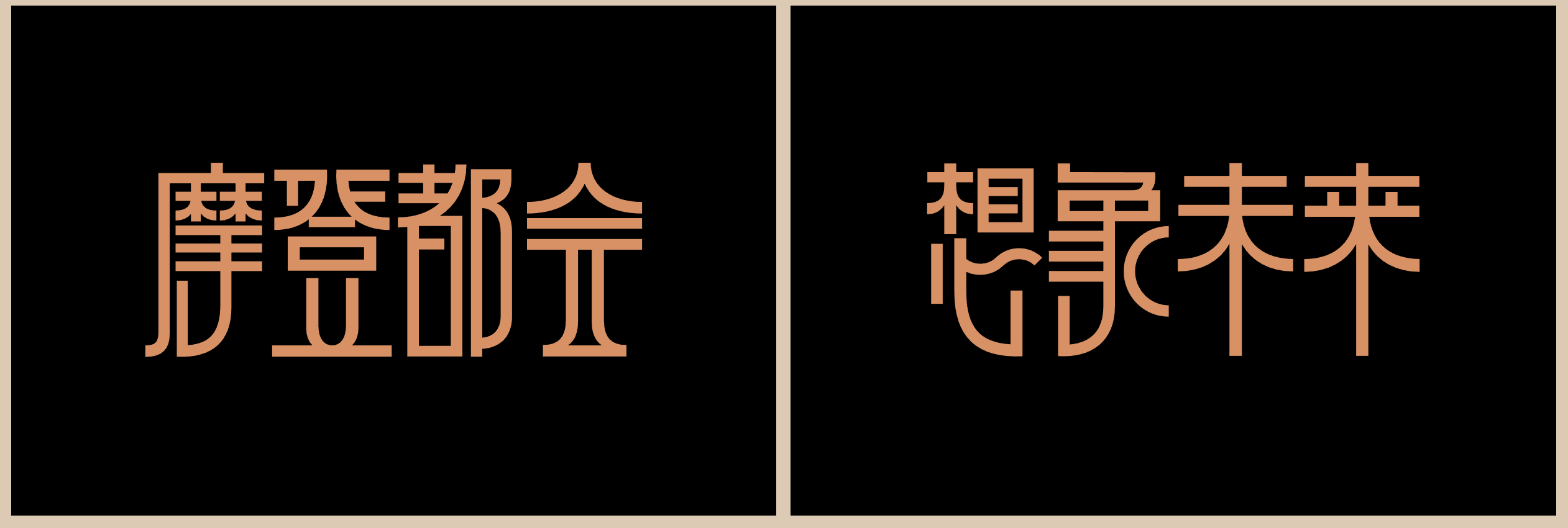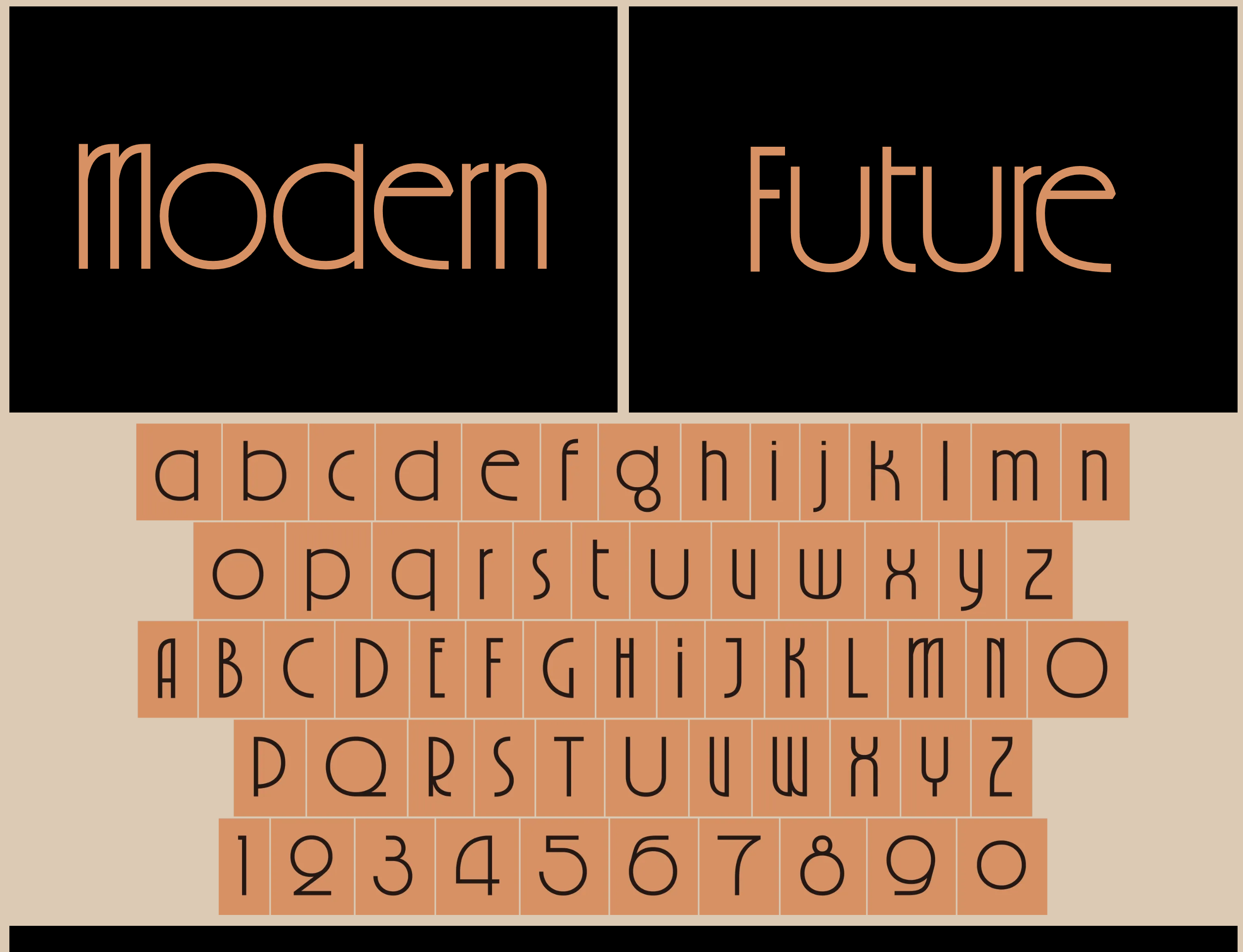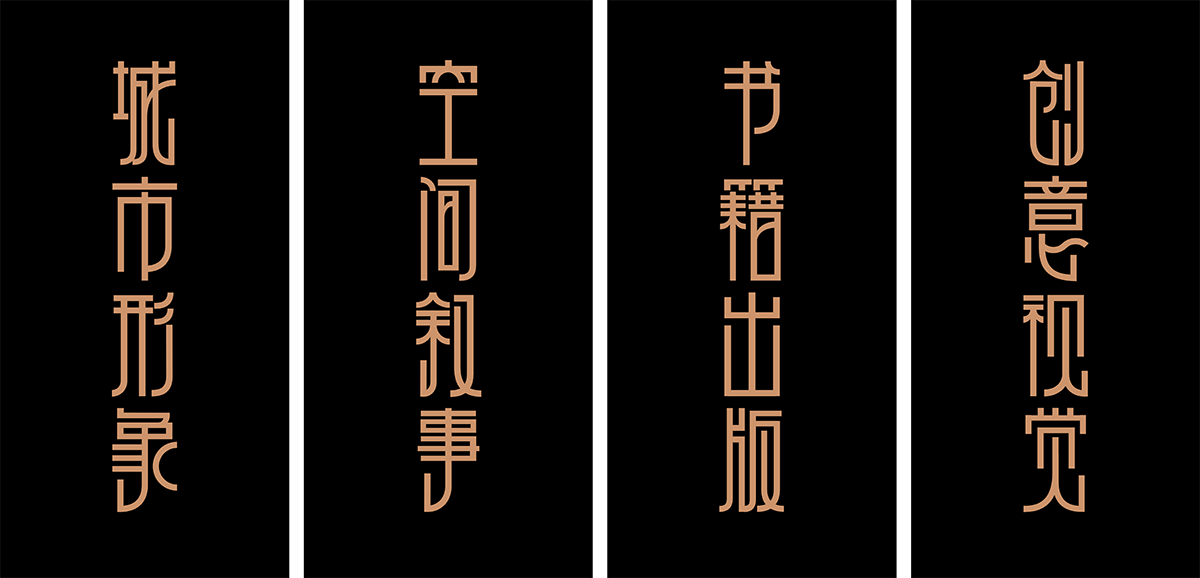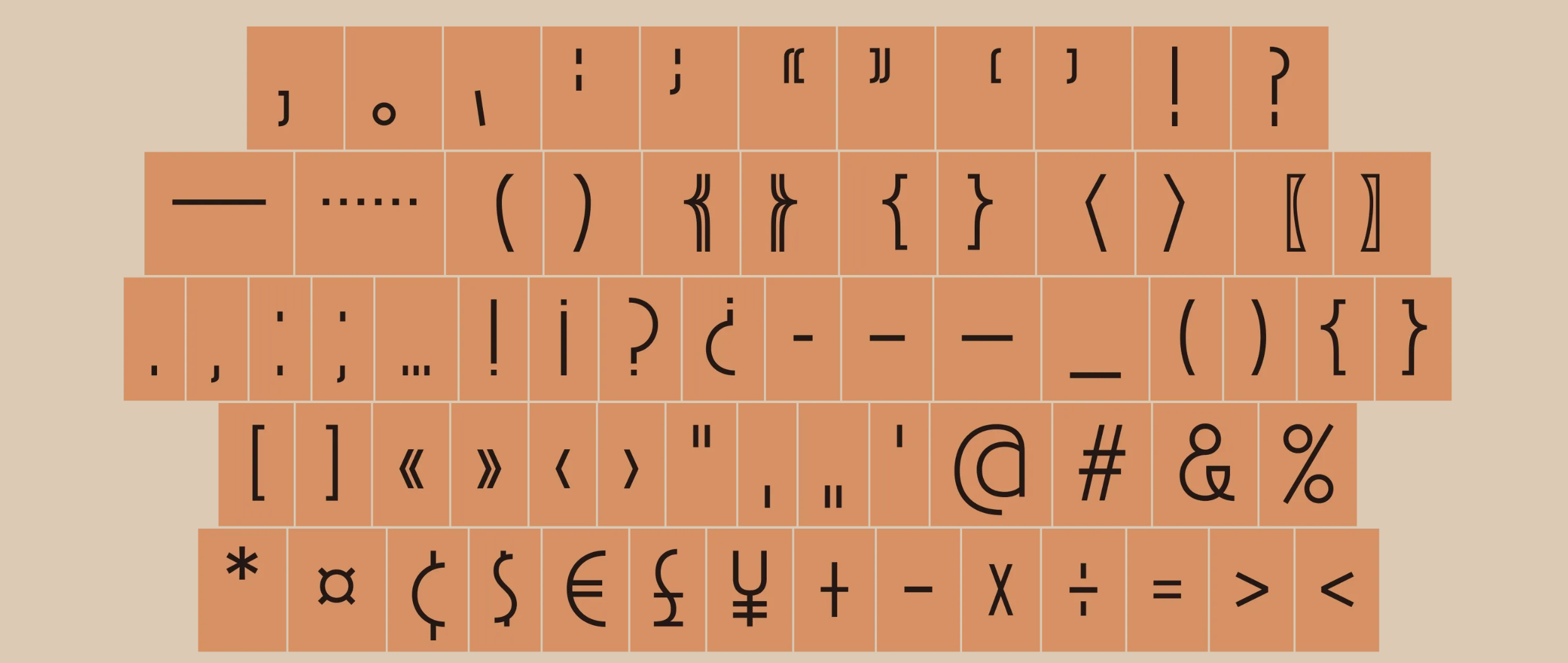
上海摩登体(Shanghai Modeng)是中国首款以城市文化为灵感源泉而设计的中西文标题字体,由汉唐文化发起研发并向社会开源共享。
该字体灵感源自 1930 至 1940 年代上海都市文化兴起时期盛行的装饰艺术(Art Déco)运动。这一时期的上海作为东西方交汇的国际都会,孕育出独具本土特色的“摩登”精神。虽脱胎于英文“modern”的音译,却并非对西方现代主义的简单模仿,而是在中国自身的文化土壤中演化出的独特视觉语言。
字形设计上,上海摩登体以现代字库技术为基底,突破传统汉字结构,将装饰艺术风格的几何美学注入到汉字中。用直线与圆弧的组合取代传统书写的自然笔触,笔画粗细均衡、刚柔相济;字体架构采用字面高耸的设计,如建筑般挺拔有力,在静态的几何秩序中迸发向上的动感,让每个字的结构都充满先锋性与想象力。
西文部分,既严格遵循与中文字体统一的设计逻辑,又充分考量西文排版的语境特征,巧妙平衡了西文字体的传统与创新。小写字母采用较高的 x 高度,特意强调圆弧造型,与窄身字母形成鲜明对比,塑造出富有几何韵律的视觉张力;同时借助 OpenType 字体技术未西文字符增加了连笔功能,让字符组合更加灵活多变、自然流畅。
阿拉伯数字部分,采用富有弹性与力度的圆弧形线条,字形精致饱满、趣味生动。标点符号的设计则延续中文字形修长的视觉特征,重心上移,冒号、分号打破常规布局,从细微之处强化了字体的独特气质。